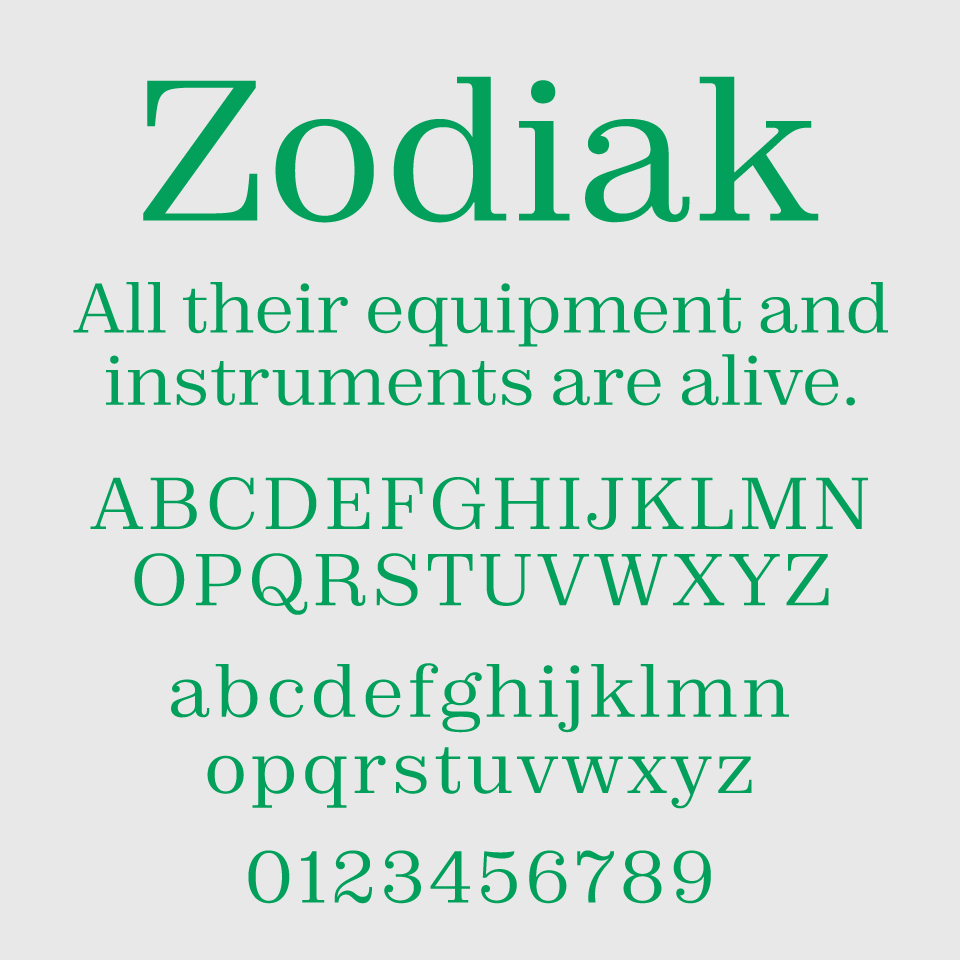
Zodiakフォントは、古典的なセリフ体に遊び心のあるひねりを加えた、知的で品のあるセリフ体フォントです。
aやgのような文字にユニークな構造が見られ、伝統的な骨格を持ちながらもどこか現代的なリズムを感じさせます。角張りすぎず、かといって丸すぎないプロポーションが、絶妙なバランスを保っている素敵なフォントです。
新聞の見出しや、学術書の表紙など、硬めのテーマにも自然に馴染みます。クラシックとモダンの間を漂うような存在で、タイポグラフィにちょっとした洒落っ気を添えたいときに活躍する幅広い場面で活用できるフォントです。